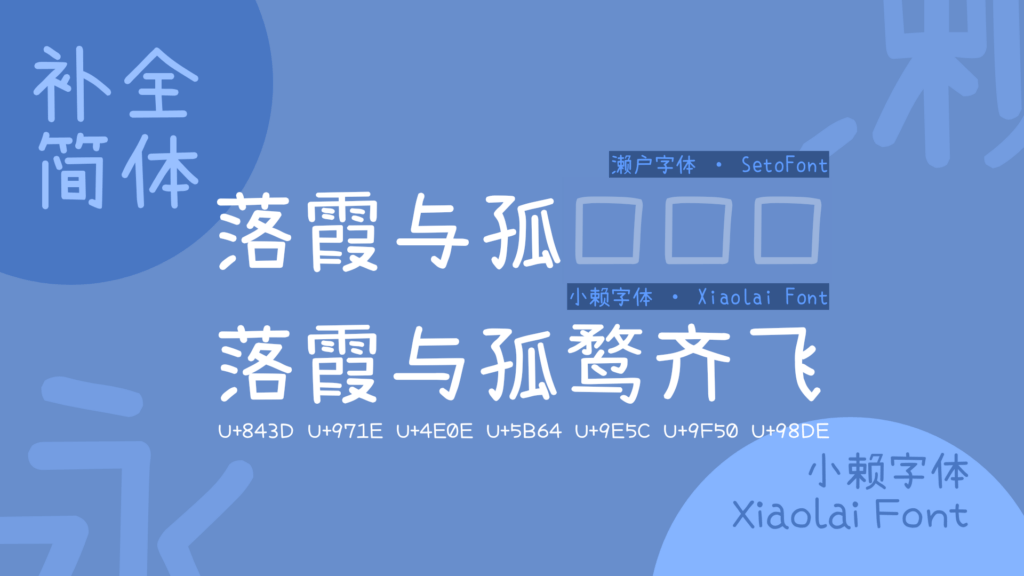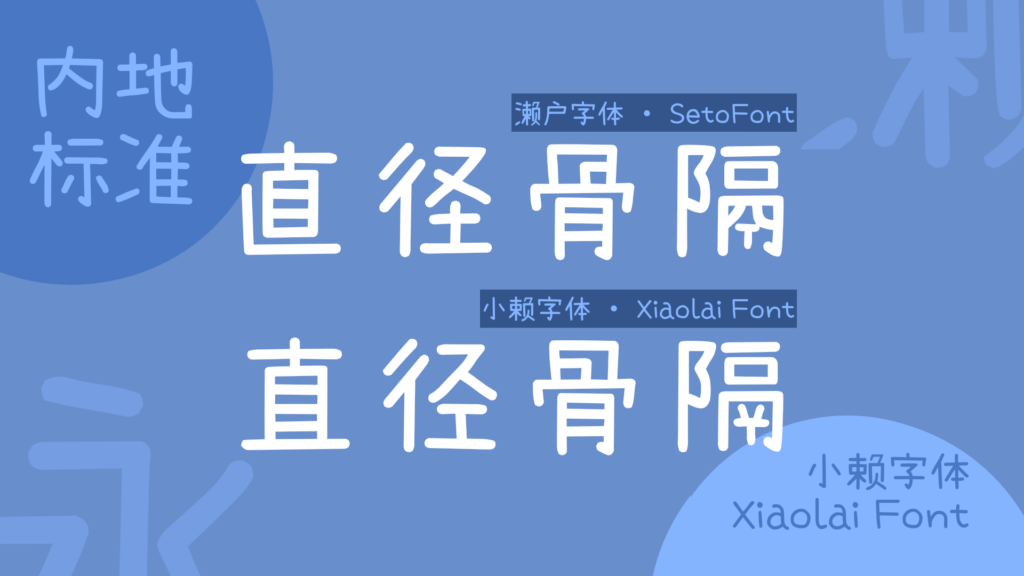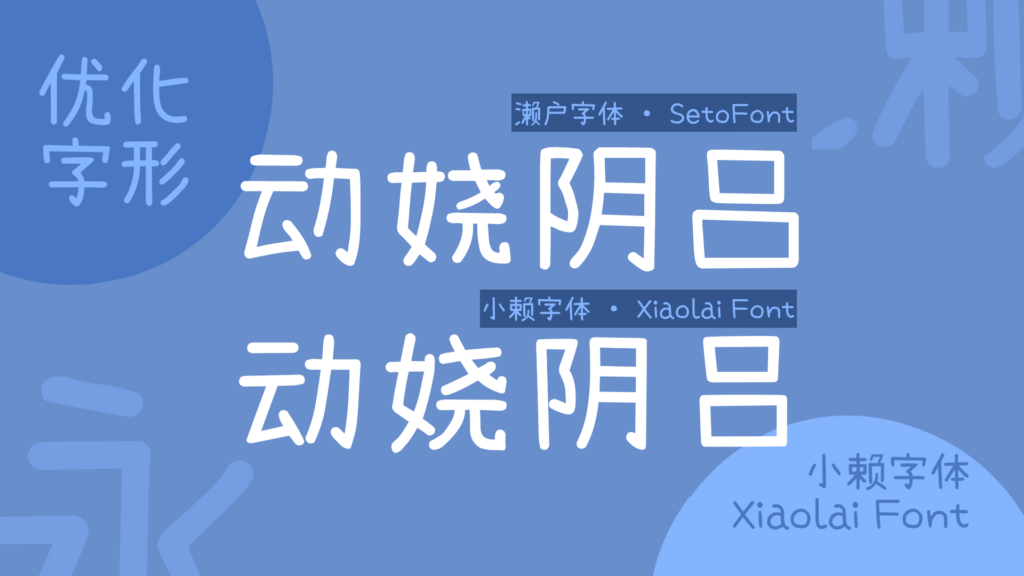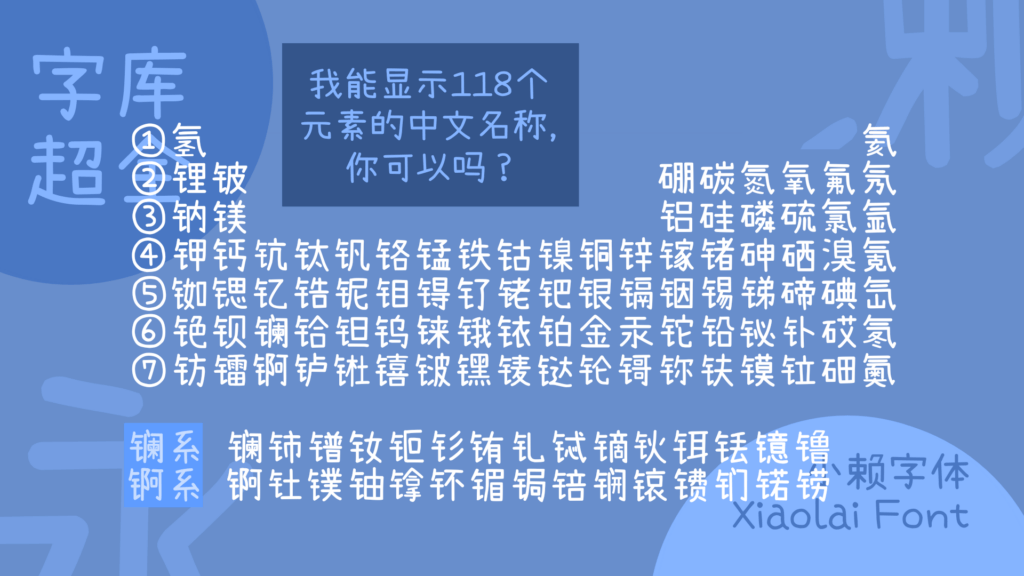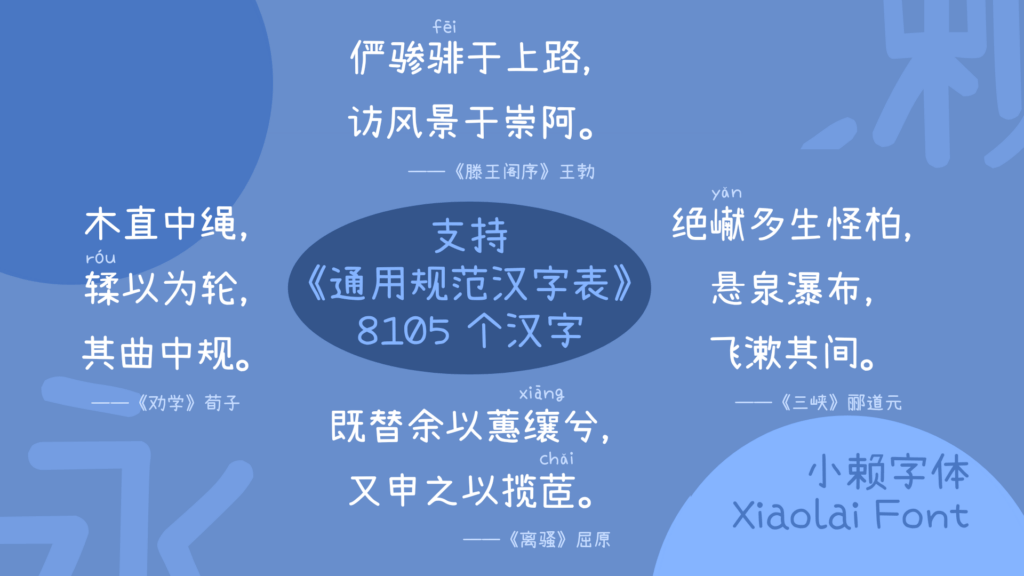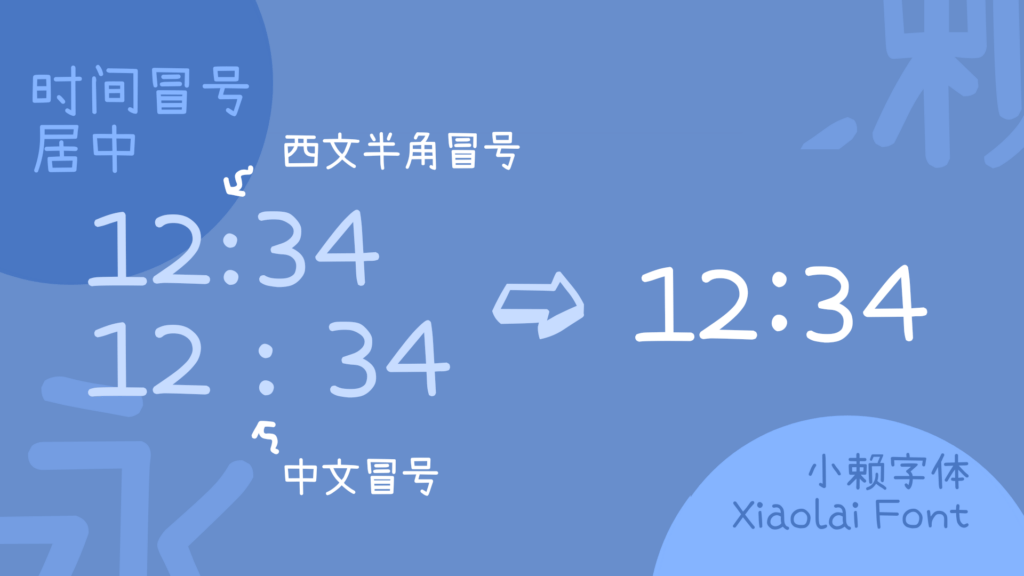
濑户字体是由日本业余字体设计师 瀬戸のぞみ独立创作的一款开源日文字体,因其清新可爱的风格而广受喜爱。该字体完整支持 *JIS 第一级至第四级 的全部日文字符,并且对 繁体中文与简体中文 提供了部分字符的支持,使其能够满足基础的中日文混排需求。其最新的官方版本为 6.20,发布于 2014 年 9 月 24 日,此后原作者便未再进行实质性更新。
由于原版字体在繁体中文地区使用时存在不少常用字缺失的问题,社区开发者 Max 在「濑户字体」的基础上,推出了 「内海字体」 这一衍生版本。该版本重点补全了 台湾教育部《常用国字标准字体表》 所列的全部 4808 个常用汉字,并且额外增加了 闽南语与粤语 的常用字,极大地完善了繁体中文的字库覆盖,使其在港台地区的可用性显著提升。
尽管如此,这款开源字体在 简体中文 方面的字符覆盖仍然不完整,缺少了大陆日常使用的一部分常见简体字,这给中国大陆的用户带来了诸多不便。为了系统地解决这一问题,由本人发起的 “濑户字体简体补全计划” 应运而生。该计划旨在通过社区协作的方式,系统性地补全「濑户字体」中缺失的所有常用简体汉字,使其成为一个真正完整支持简体中文的开源字体。
小赖字体 正是这一补全计划的重要成果与延续。该项目最初定名为 「小濑字体」,但考虑到在中文社区中,许多用户因输入法或认知习惯容易将「濑」字误输入为「赖」字,为了便于传播、降低使用门槛并增加项目的亲和力,项目负责人最终决定将字体名称中的「氵」部首去掉,正式更名为 「小赖字体」。这一更名不仅解决了混淆问题,也使得字体名称在中文语境下更加朗朗上口、易于记忆。